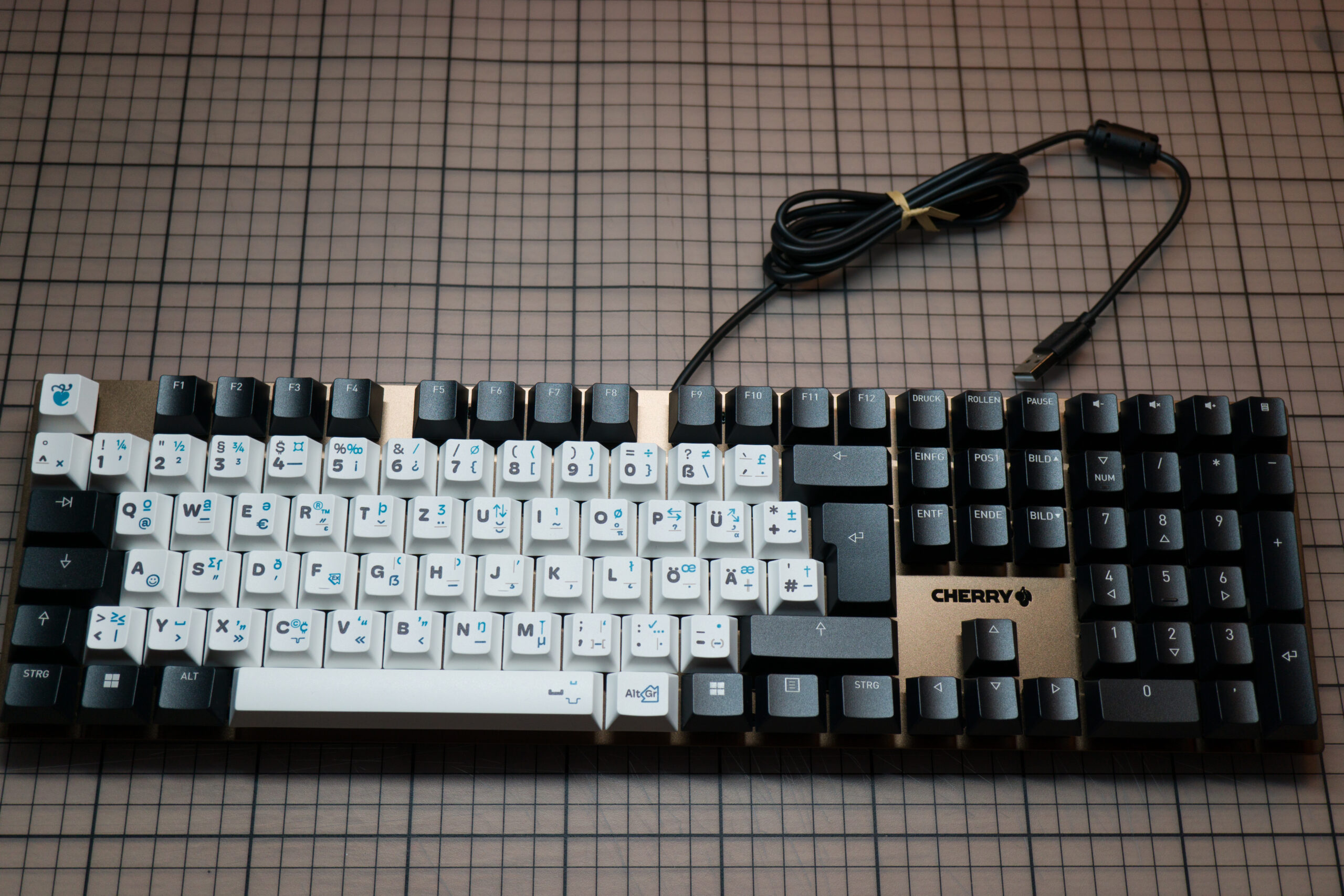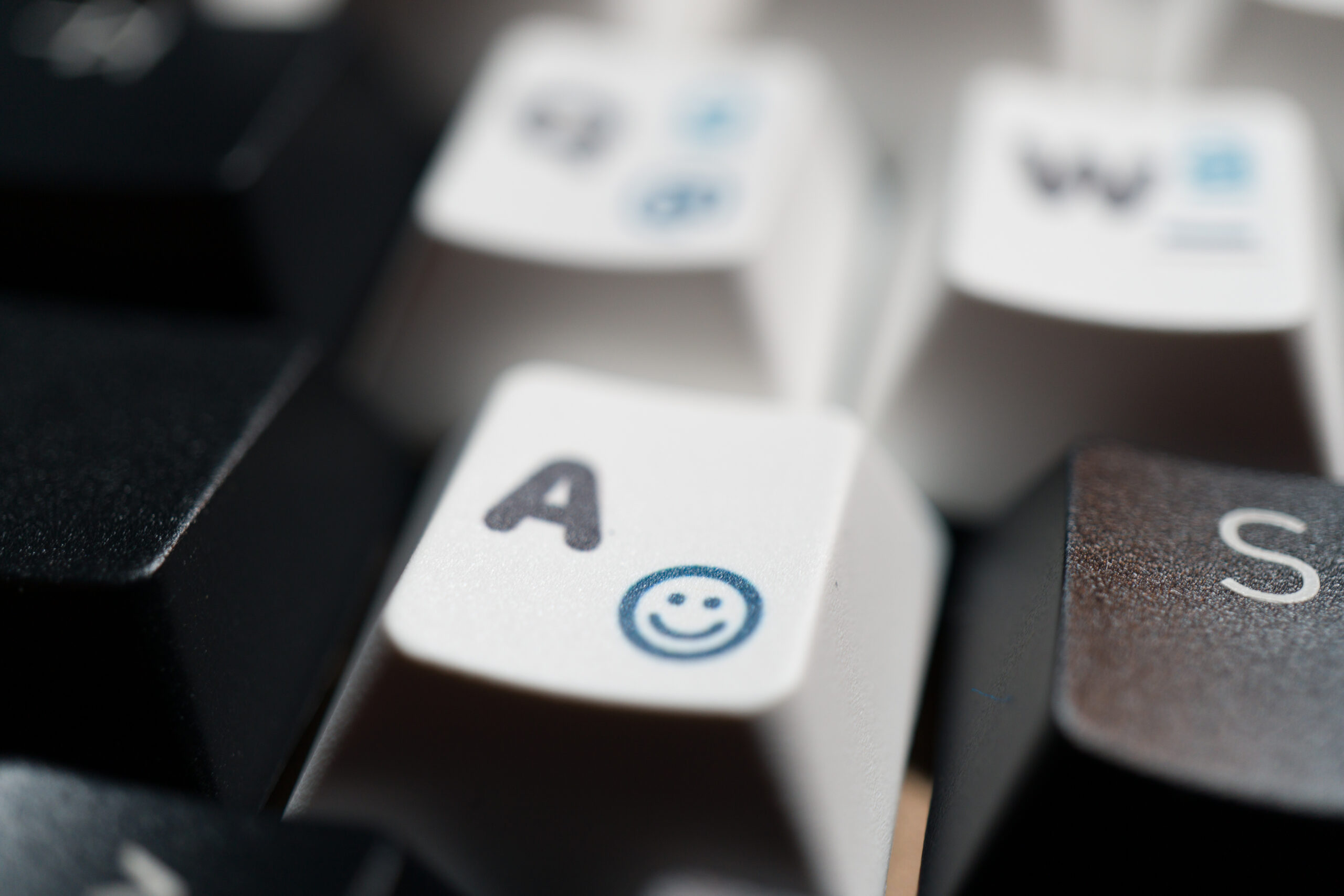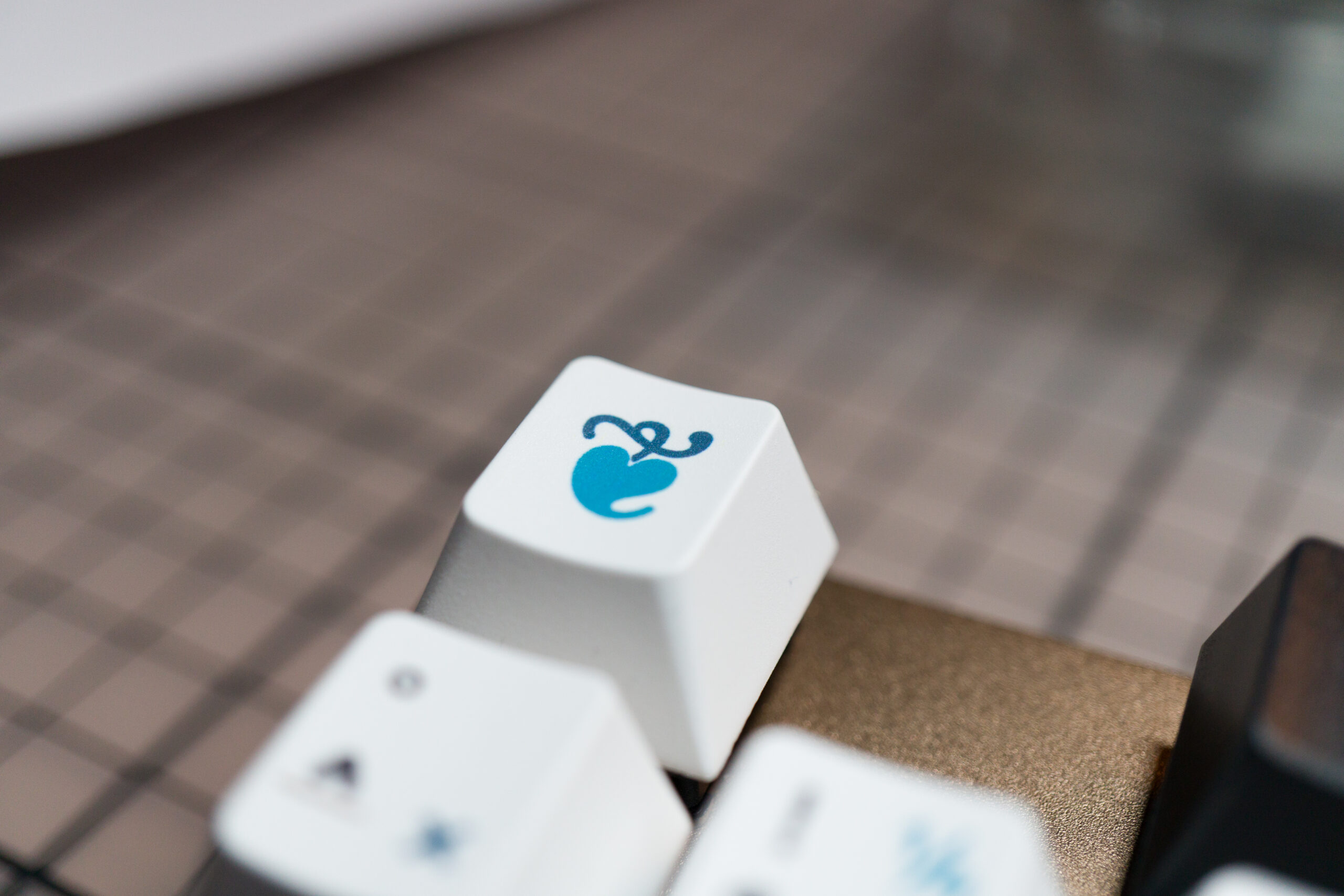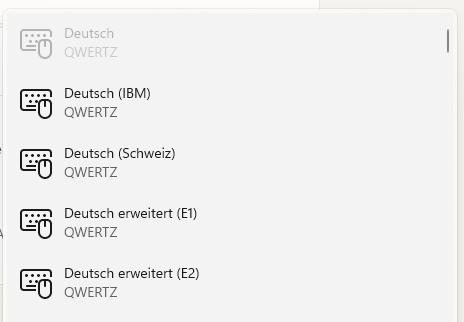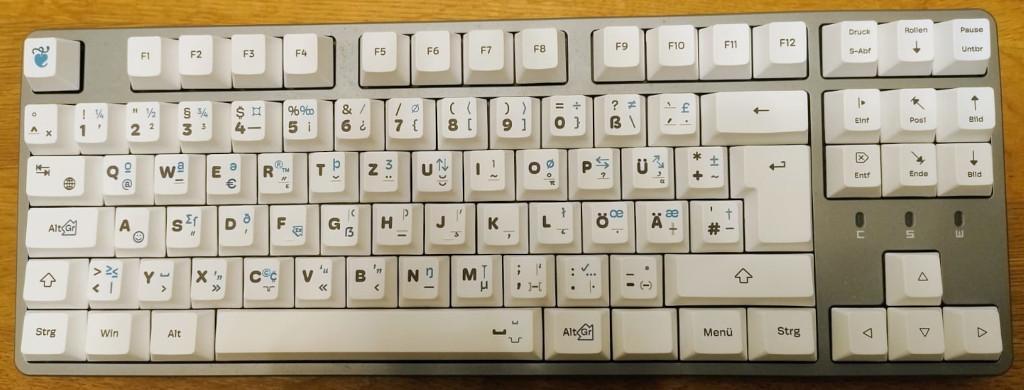
Gibt es E1-Tastaturen mit aufgedrucktem ẞ?
Das mit den Feststelltasten ist ein bekanntes Problem zwischen verschiedenen Tastaturtypen, echt ärgerlich.
Auch Leertasten sind immer mal für eine Überraschung gut, hier wurde ja schon etwas Vorsorge getroffen.
Habe meine jetzt einen Tag in Gebrauch, macht wirklich Freude. Meine Güte, knallen die alphanumerischen Hauptbeschriftungen rein — aber sie müssen sich ja auch gegen den Rest durchsetzen…
Hier ist sie, mit einer »Fremdtaste« (auf der Position für die Steuerung der von mir eh nicht genutzten Beleuchtung) :
Ein kleiner Wermutstropfen ist dabei, meine Feststelltaste ist nicht symmetrisch und auch die Aufnahme des Kreuzes ist nicht mittig. Das ist für mich überraschend, aber tut meiner Freude insgesamt keinen Abbruch.
Meine Empfehlung ist in diesem Fall, gleich mehrere oder alle Steuertasten unangetastet zu lassen. Das sieht eigentlich auch ganz schick aus und vermeidet, dass nur eine einzelne Taste wie ein Fehler raussticht.
Jetzt hat das Windows11-24H2-Update auf einen meiner Rechhner gefunden, und siehe da, E1 und E2 sind da :-)
So blind tippt es sich damit etwas schwierig, aber prinzipiell funktioniert es.
1 ! ’ ¼
... einfach so getippt :-)
Die Capslock-Taste bleibt aber offenbar Capslock und wird nicht zur zweiten AltGr ... da muss ich noch ein bisschen rescherschieren ...
Ja, soweit wollte man leider nicht gehen. Bei europatastatur.de bekommt man die Variante mit zweiter AltGr-Taste.
Werd ich mal ausprobieren - natürlich wäre mir eine native  Lösung lieber, aber im Treiber steckt vermutlich mehr Praxisbezug drin, als Microsoft da jetzt mal rein steckt ... vielleicht kommt da ja noch was.
Als Alternative fiele mir jetzt (bei keychron) ein, per VIA auf die Capslock-Position nochmal den Keycode von AltGr zu legen - genau dafür ist das ja gedacht. Dann bekommt das Betriebssystem von der Tastatur die Info, dass "altGr" gedrückt worden sei, und kann gar nicht anders als entsprechend zu handeln.
Hat eigentlich Apple zu E1-Support je irgendwas in Aussicht gestellt?
Die Typotasten sind bei mir eingetroffen. Fast gleichzeitig mit den Kailh-Brown Switches; siehe:
Bei den Kailh Browns wird ein um 10 gf (also 20 %) höherer Operating-Force-Wert angegeben – ob das den großen Unterschied macht?
Ja, es macht einen Unterschied. Der höhere Widerstand wirkt auf mich einfacher zu kontrollieren. Leider sitzen die Tasten dafür auch etwas schwammiger auf dem Switch, was die Wertigkeit wieder herunterzieht. Aber ich bleibe erst mal dabei.
Die Typotasten selbst sind prima. Mit einem schwarzen Board wirken sie recht bunt, aber sie haben was. Die Haptik ist auch sehr angenehm.
Die originalen F-Tasten der Tastatur habe ich bisher noch nicht ausgetauscht, weil ich die Sekundärfunktionssymbole (Lauter, leiser, heller, dunkler etc.) praktisch finde und eigentlich nicht darauf verzichten will. Aber früher oder später wird der visuelle Anspruch siegen und auch hier auf die weißen TypoTasten bestehen.
Jetzt hat das Windows11-24H2-Update auf einen meiner Rechhner gefunden, und siehe da, E1 und E2 sind da :-)
Das klingt gut. Bei mir ist seit dem 23H2-Update von letzter Woche nichts mehr passiert. Ich hoffe, dass sich das demnächst ändert; denn der Europatastatur-Treiber funktioniert bei mir nur sehr begrenzt.
Einiges (z. B. ›»ẞ«‹—−) funktioniert prima. Caps Lock ist aber immer noch Caps Lock und alles mit Tottasten und verschiedene andere Zeichen werden gar nicht generiert.
Edit: Țºŧtªstẹn und weitere Zeichen funktionieren bei mir, aber nicht über [Alt Gr], sondern nur über [Strg] + [Alt].
Nachtrag zu [Alt Gr] bzw. [Strg] + [Alt]
Ich habe vorhin meiner neuen Tastatur Typotasten verliehen, und bin im Moment einfach glücklich. Für den Treiber unter Windows 11 nahm ich die Version v3.02, weil bei der noch der Smiley vertreten ist, der mir einfach ans Herz wuchs. Hier ein paar Bilder:20241129-0002-typotasten-2-scaled.jpg20241129-0006-typotasten-scaled.jpg20241129-0010-typotasten-scaled.jpg20241129-0017-typotasten-scaled.jpg20241129-0019-typotasten-scaled.jpg20241129-0021-typotasten-scaled.jpgIch entschied mich für die »Marke« für die Esc‑Taste, und für diese Mischung aus Typotasten und Originalkasten der Tastatur, auch aus Gründen des Oldschool. Der Klang der empfohlenen Cherry ist vor allem bei der Leertaste einfach toll ☺
Falls übrigens jemand aus einem Umbau einen kompletten Satz konventioneller alphanumerischer Tasten günstig abzugeben hat, bin ich für ein anderes Bastelprojekt interessiert (PN, bitte).
Aber gebt die nicht leichtfertig ab, bitte — nicht, dass ihr später mal rückbauen wollt und euch ärgert.
Kurzum, es gibt viele gute Gründe für die entstandene Lösung und sie ist nicht nur einer »Meinung« wegen entstanden.